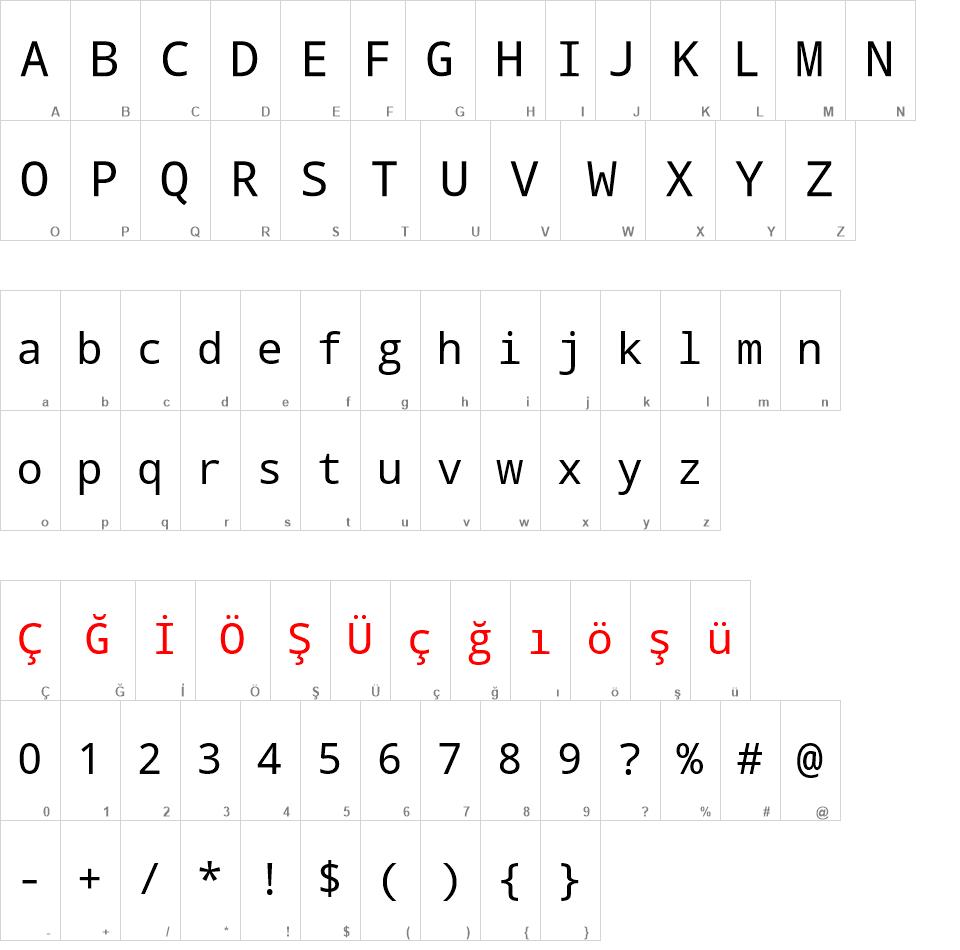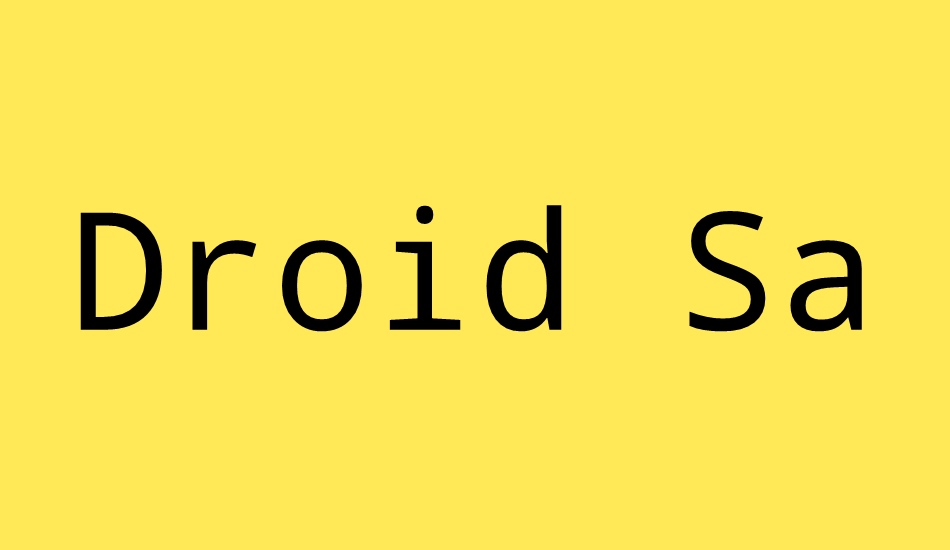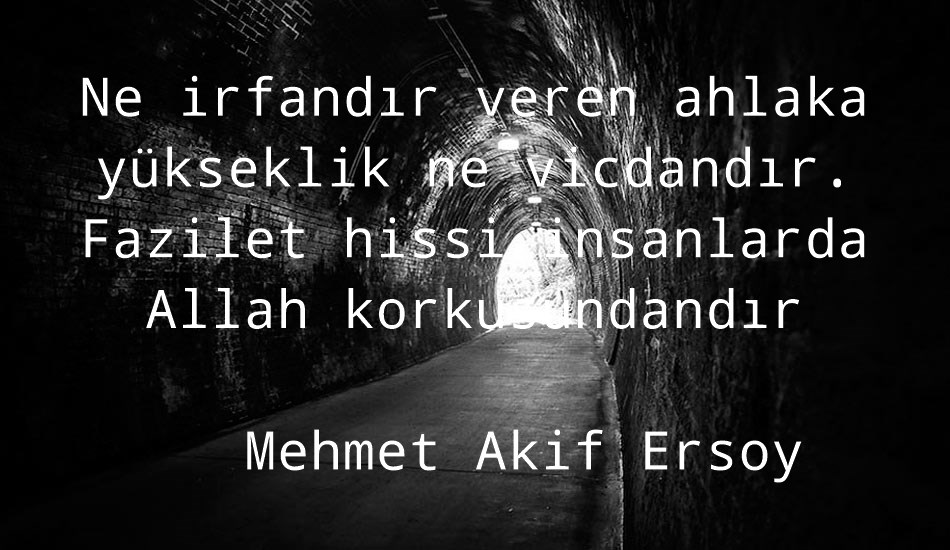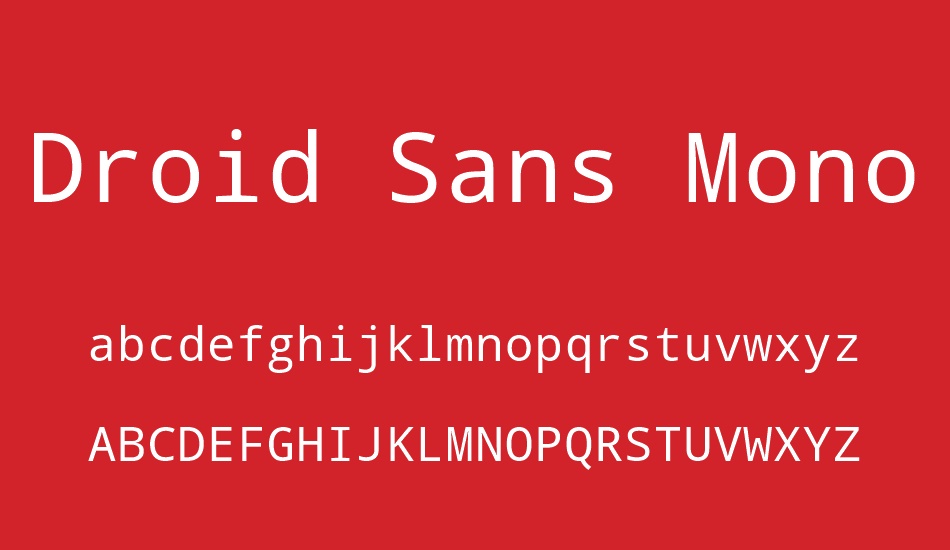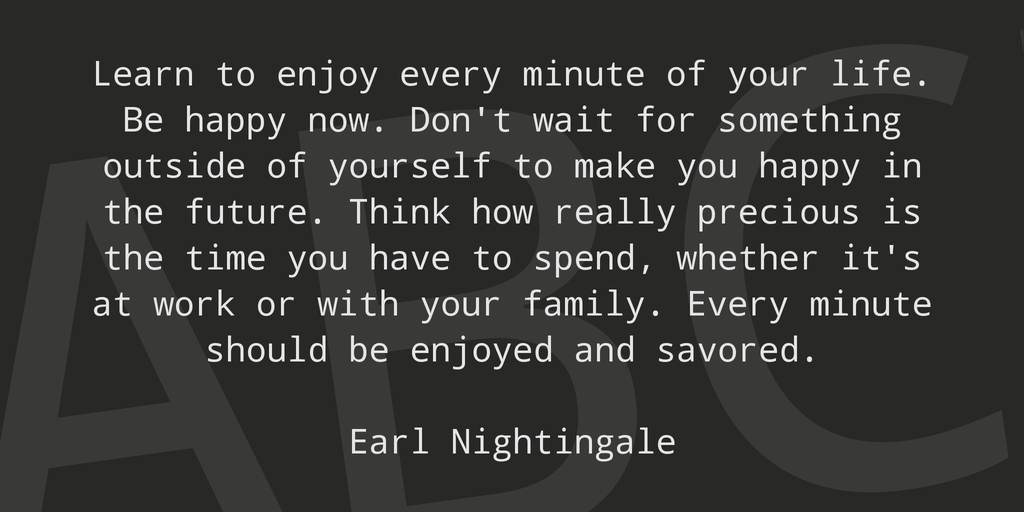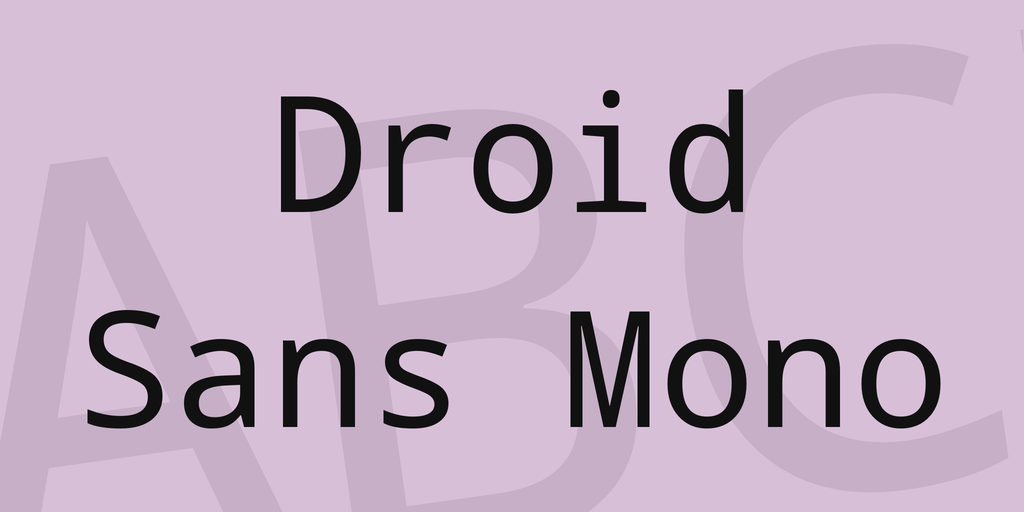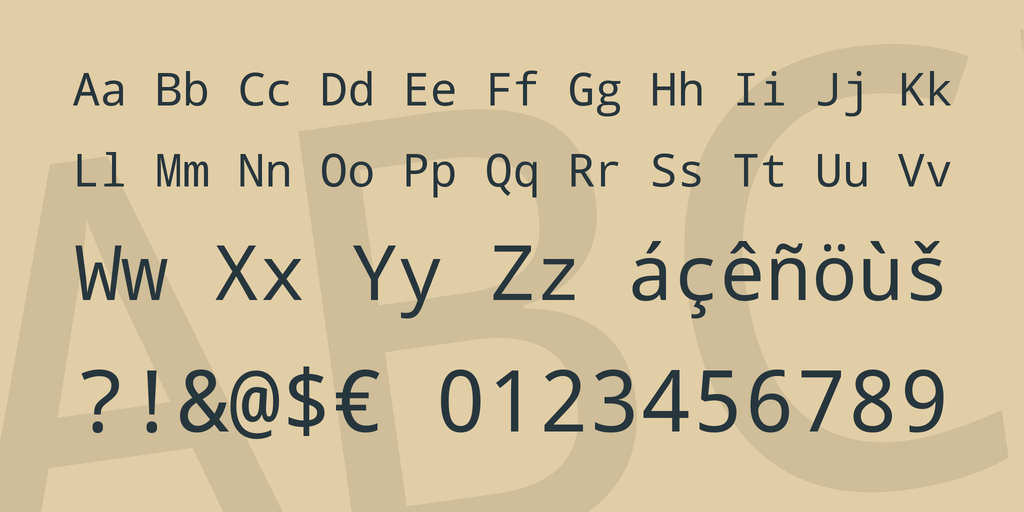
Droid Sans Mono Font font
Droid Sans Mono, Droid Sans'ın sabit genişlikte bir versiyonudur. Droid Sans Mono font yazı karakterleri, Ascender Corp.'un Steve Matteson tarafından tasarlanmıştır. Droid Sans Mono yazı tipleri, metni bir tablo biçiminde görüntülemek için orantısız aralığı ve monospaced bir fontun arzu edildiği diğer kullanımları içermektedir. Droid Sans Mono, harf formlarında mükemmel okunaklılık özelliklerine sahiptir.